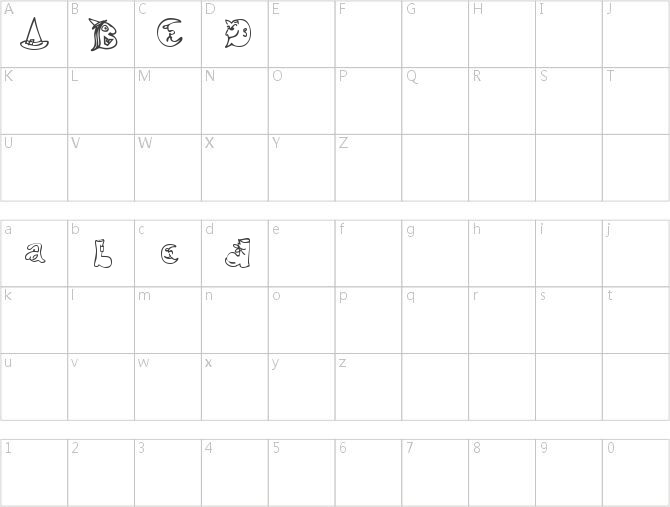
Halloween Match Unregistered 詳情頁
Halloween Match Unregistered字體字庫是一款讓人賞心悅目、百看不厭的英文字體,適合各類廣告和產(chǎn)品包裝設(shè)計應(yīng)用,字體大小0.01MB,格式為ttf字體,上傳用戶是17199970014,作者/版權(quán)方為未知